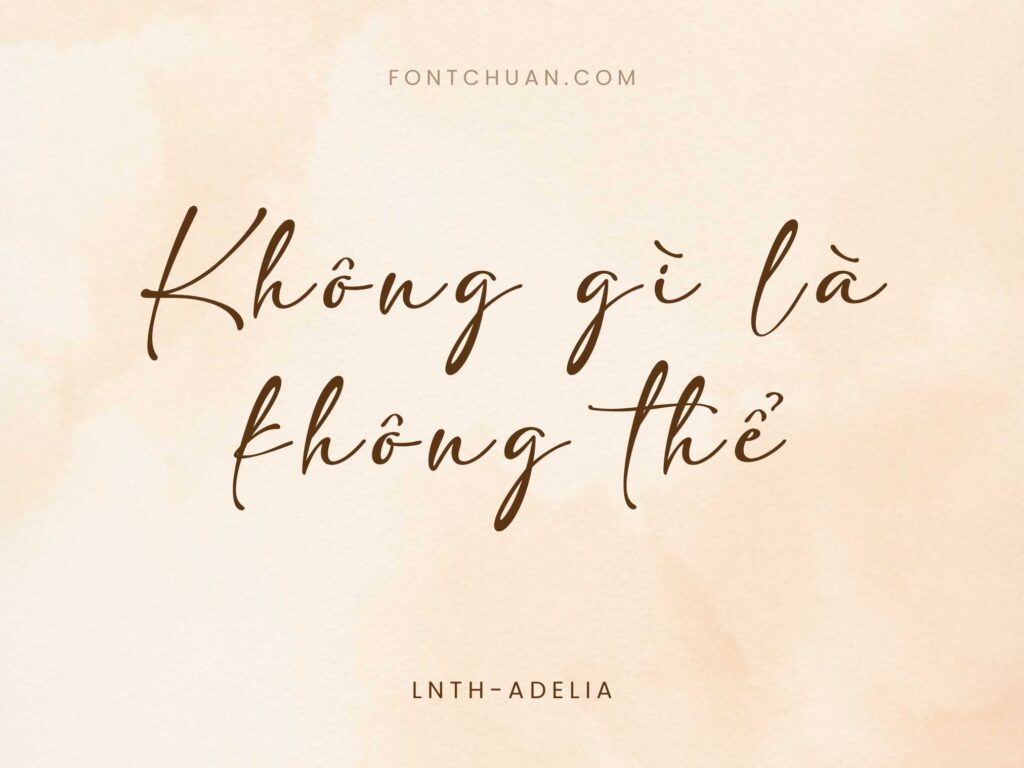
Font LNTH Adelia Việt Hóa
Tác giả Font: Carroline Herrera
Adelia là một phông chữ thư pháp đầy tinh tế, mang phong cách viết tay mềm mại và quyến rũ. Thiết kế của phông chữ này giúp tạo ra sự thanh lịch và uyển chuyển, phù hợp cho nhiều dự án sáng tạo. Phiên bản Việt hóa của LNTH giúp hỗ trợ đầy đủ các ký tự tiếng Việt, mang đến trải nghiệm sử dụng mượt mà trong các thiết kế đa ngôn ngữ. Phông chữ này được sưu tầm và đăng tải bởi thành viên của Font Chuẩn nhằm đáp ứng nhu cầu đa dạng của cộng đồng thiết kế.
Về đặc điểm thiết kế, Adelia có các ký tự được vẽ tỉ mỉ với những đường nét mượt mà, tạo nên phong cách thư pháp nhẹ nhàng nhưng không kém phần sang trọng. Phông chữ này đặc biệt phù hợp cho các dự án như thiệp mời, bìa sách, poster, logo và các ấn phẩm quảng cáo, giúp truyền tải sự tinh tế và nghệ thuật. Ngoài ra, Adelia cũng thích hợp cho các sự kiện như lễ hội, sinh nhật, Valentine và Trung thu, mang đến không gian lãng mạn và ấm áp. Trong lĩnh vực ngành nghề, phông chữ này được ứng dụng rộng rãi trong quảng cáo, thiết kế thiệp cưới, giáo dục và công nghệ, góp phần tạo điểm nhấn độc đáo và chuyên nghiệp cho các sản phẩm và thương hiệu.